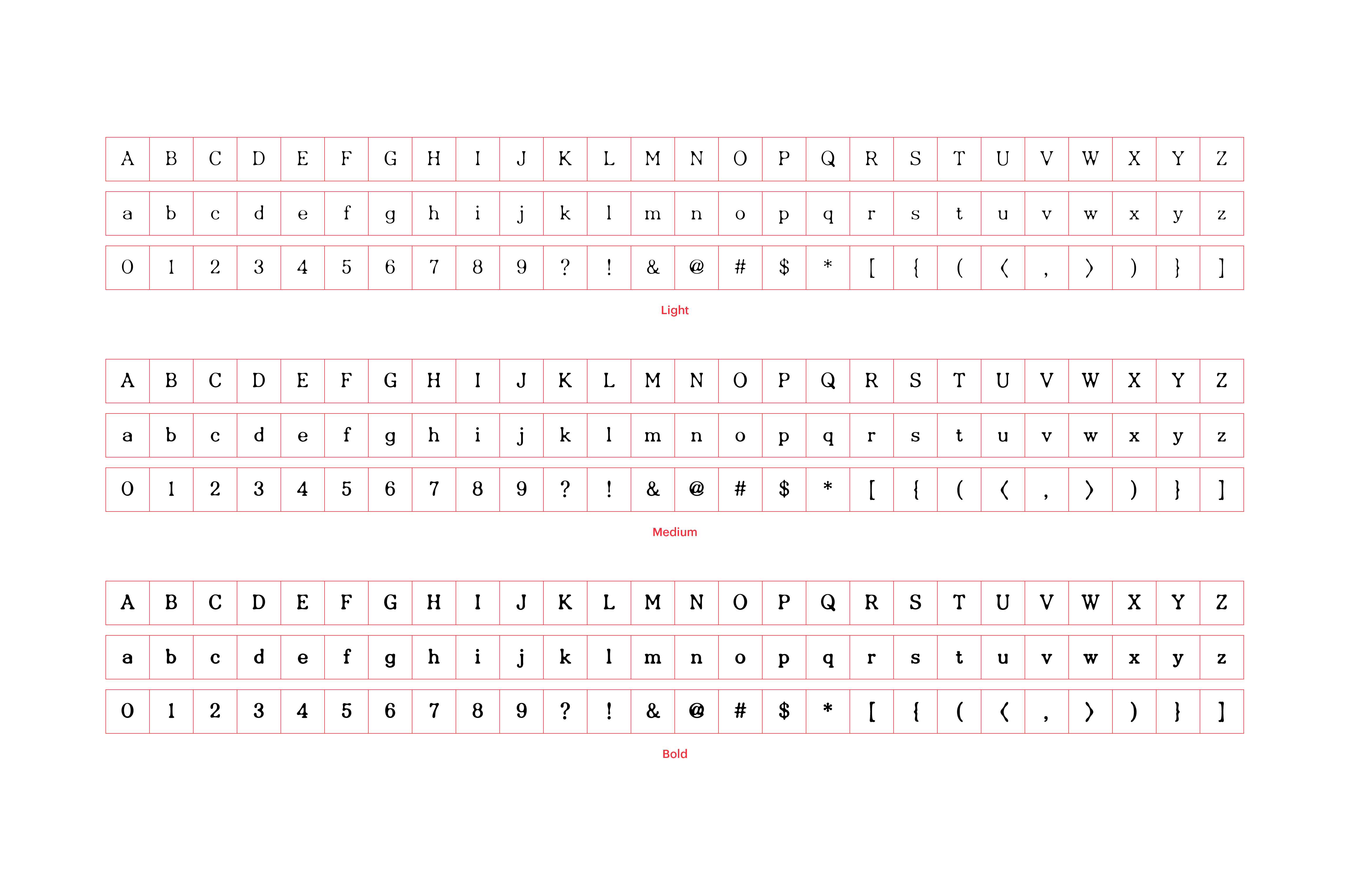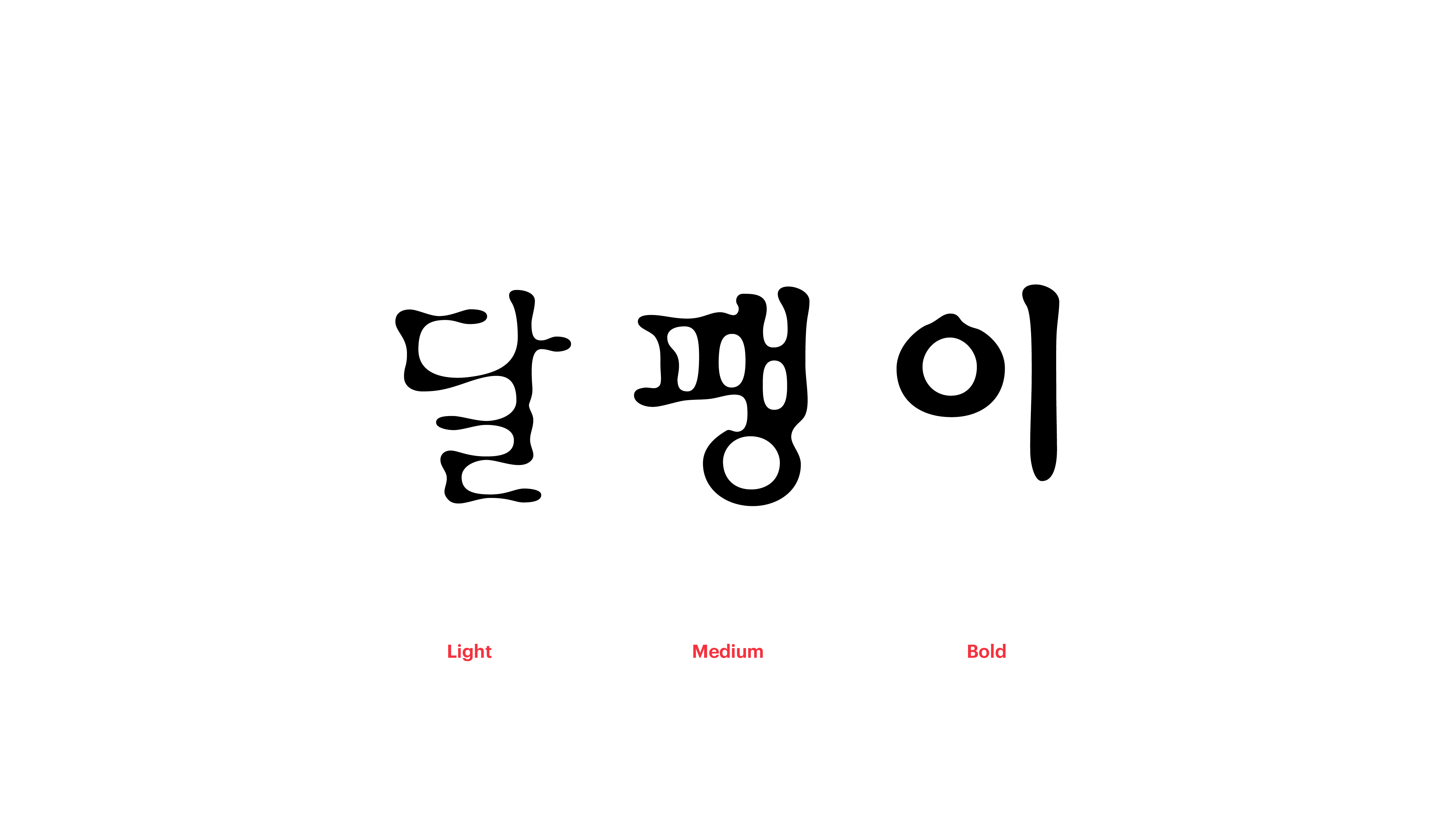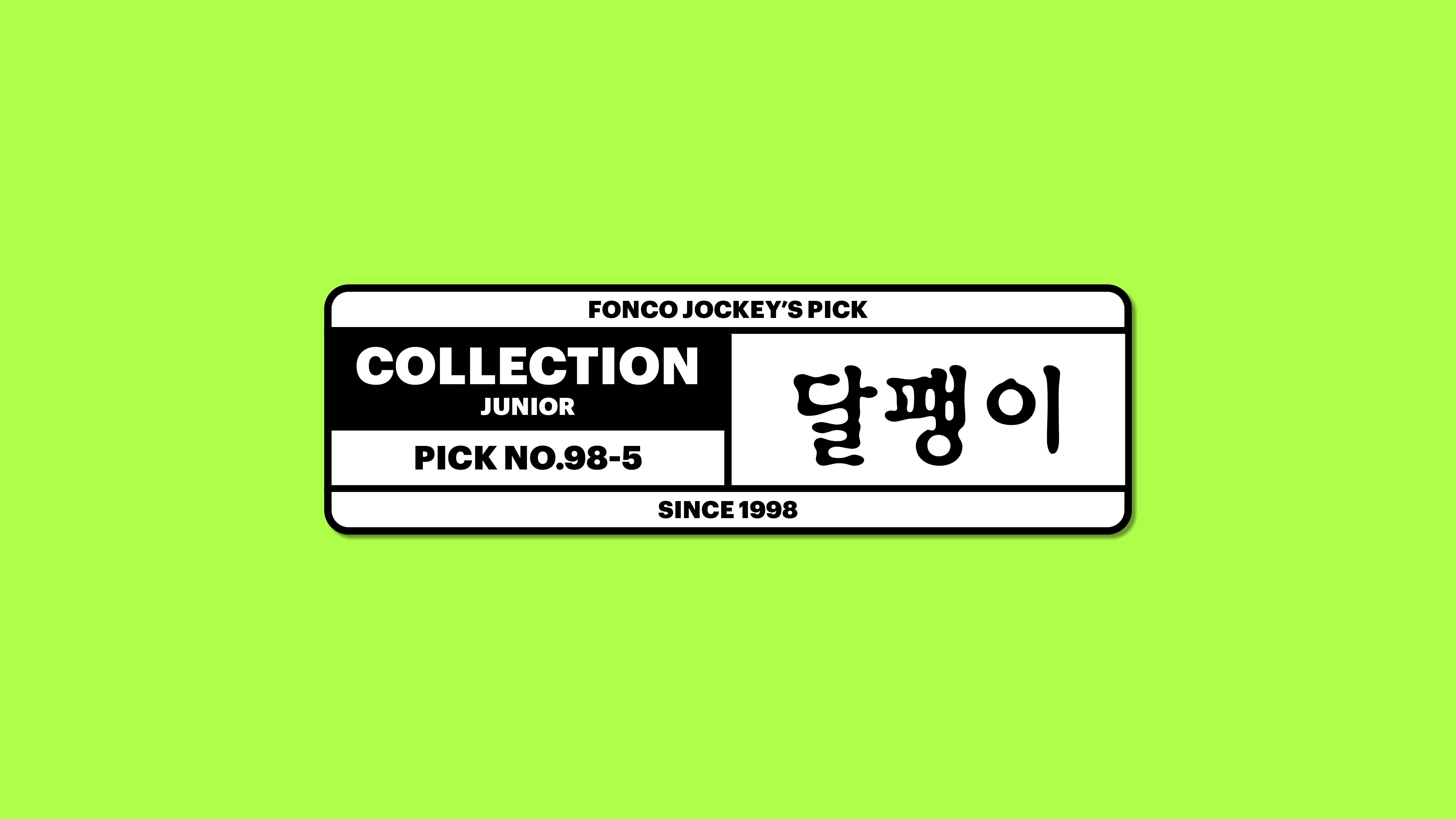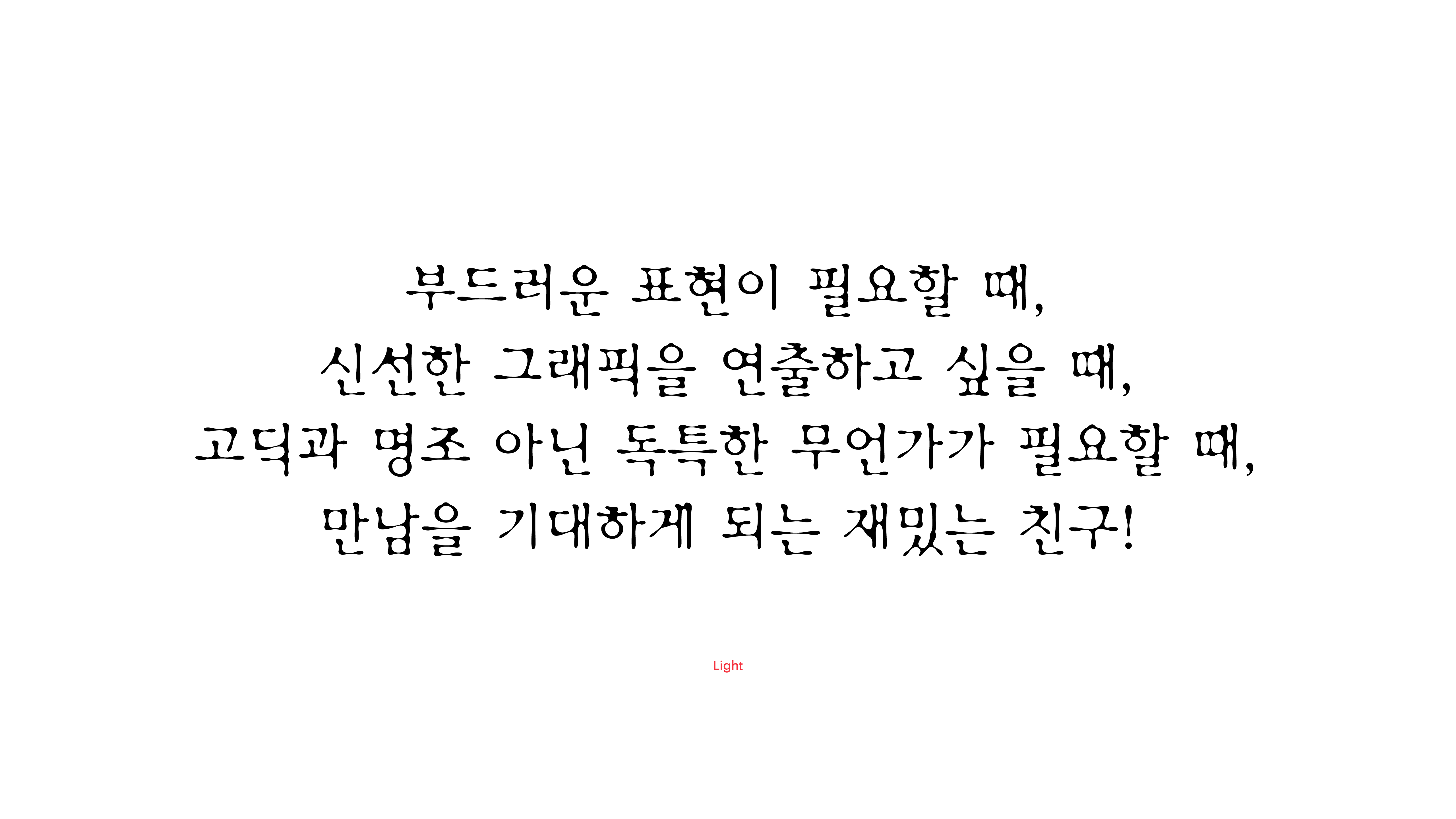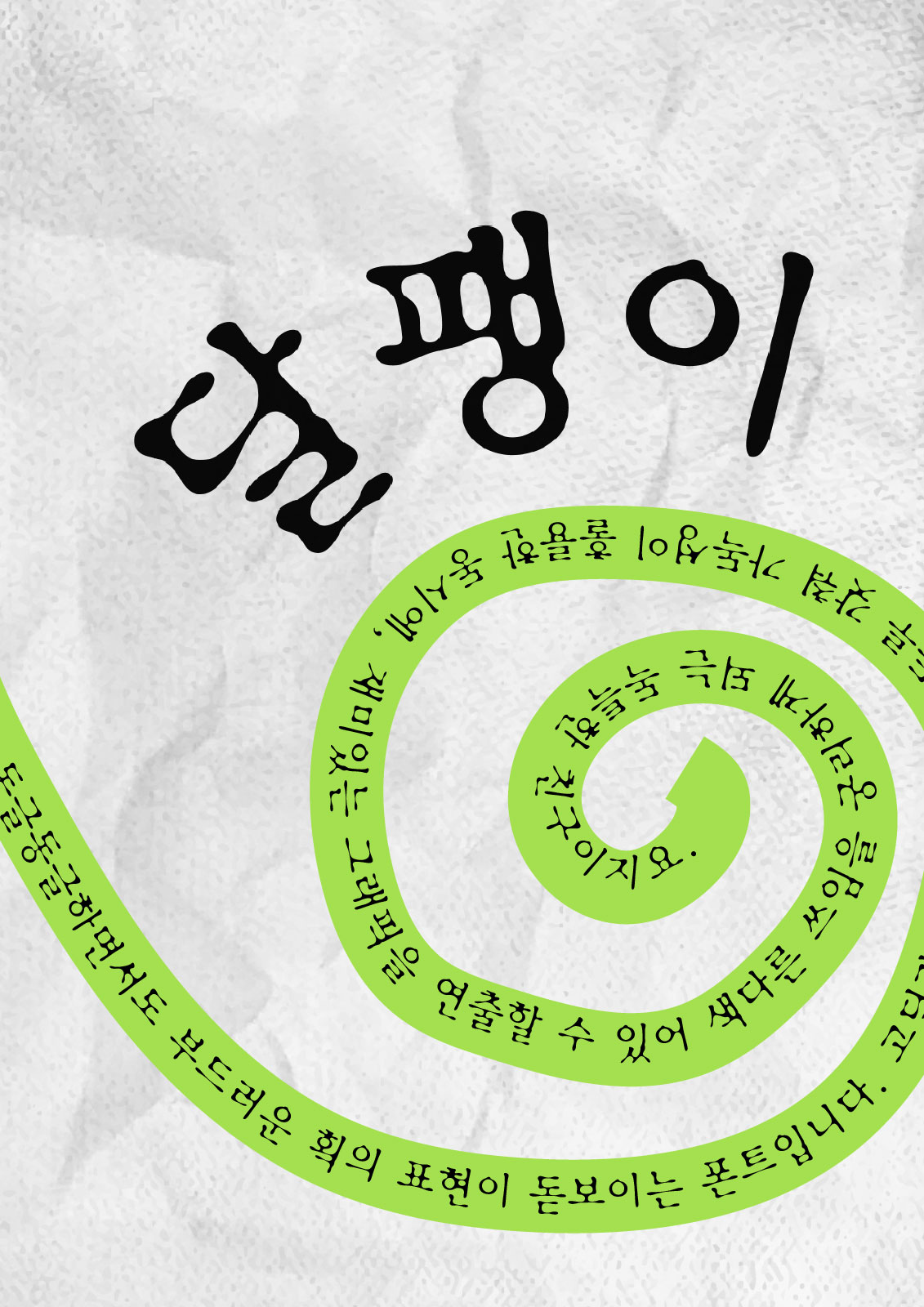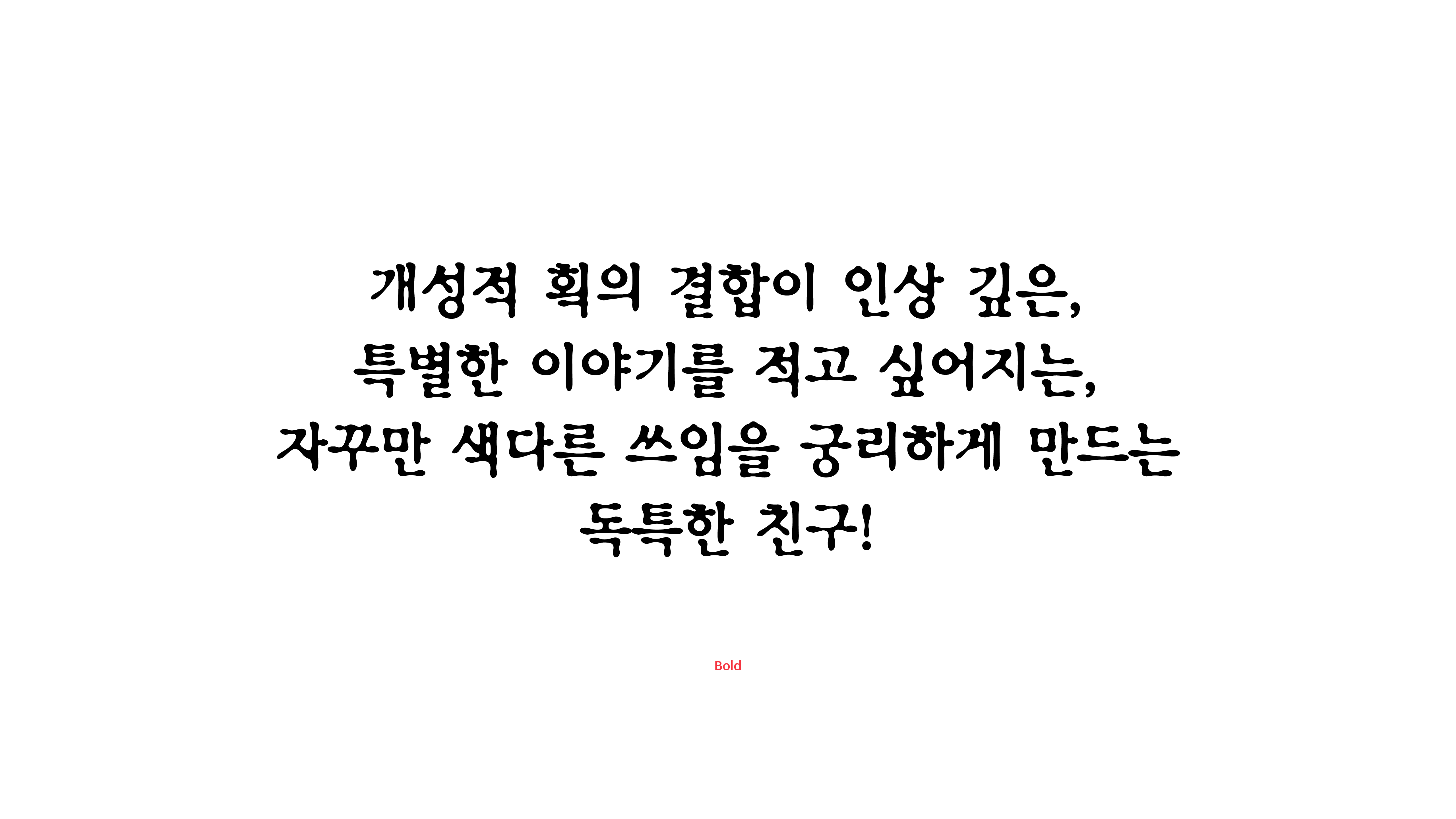
달팽이
Yoon 달팽이
쭉쭉 뻗어나가는 유연한 달팽이의 촉수. 마치 그 촉수들이 찰싹 붙어 획을 이루듯 동글동글하면서도 부드러운 획의 표현이 돋보이는 폰트입니다. 고딕과 명조의 매력을 두루 갖춰 가독성이 훌륭한 동시에, 재미있는 그래픽을 연출할 수 있어 색다른 쓰임을 궁리하게 되는 독특한 친구이지요.